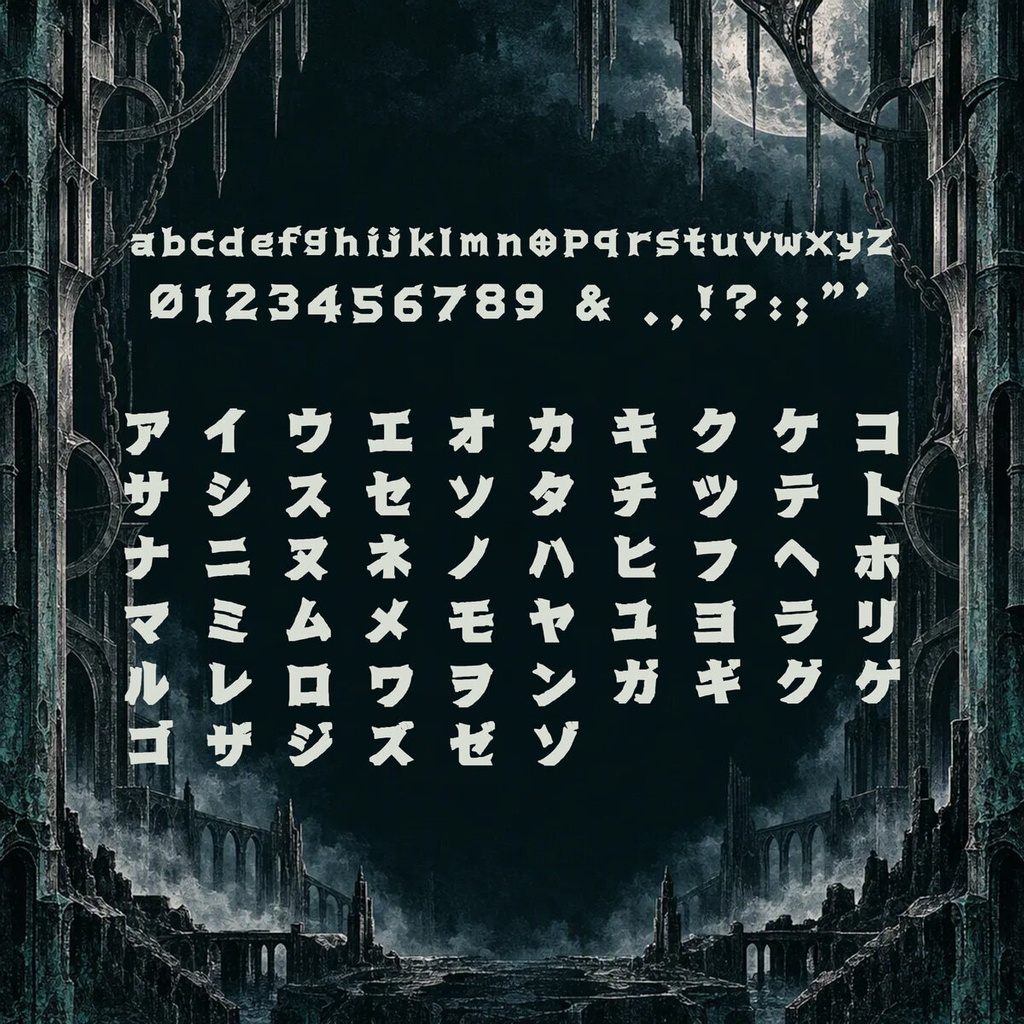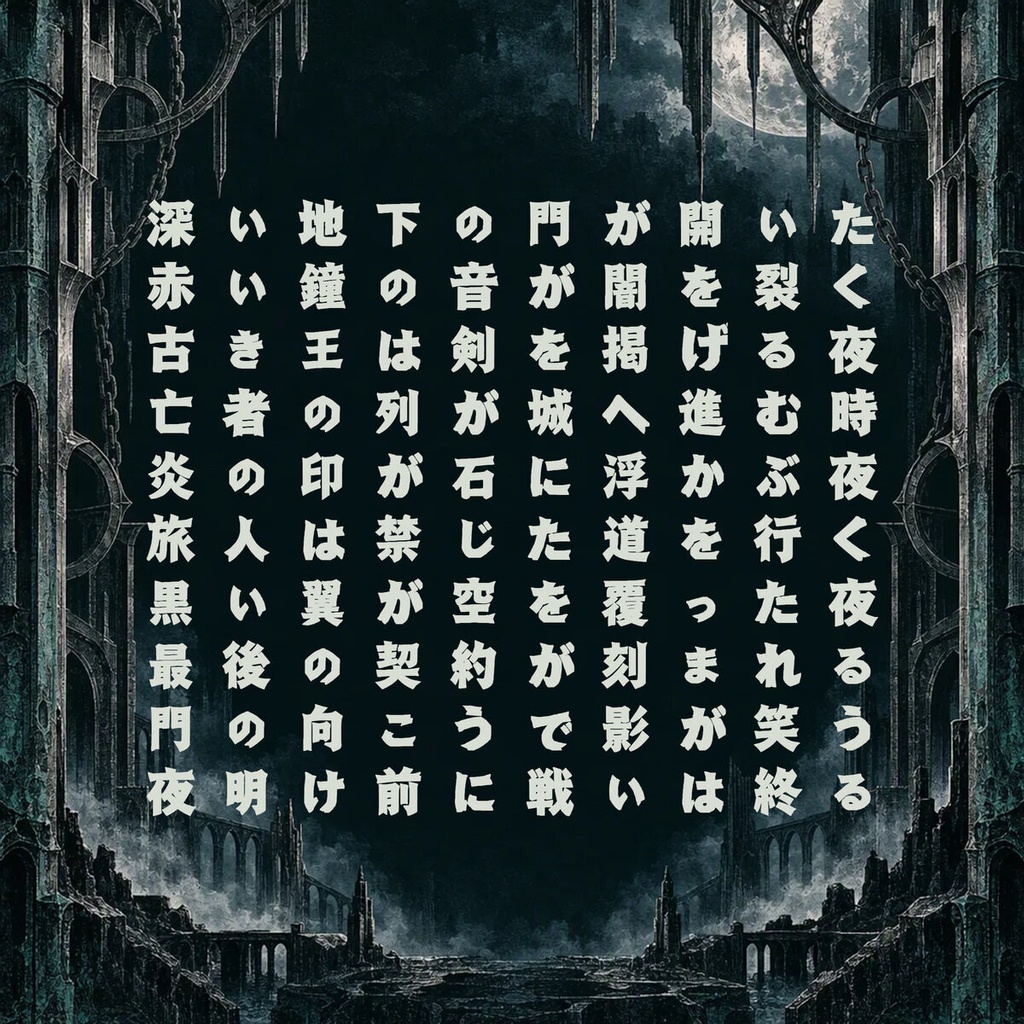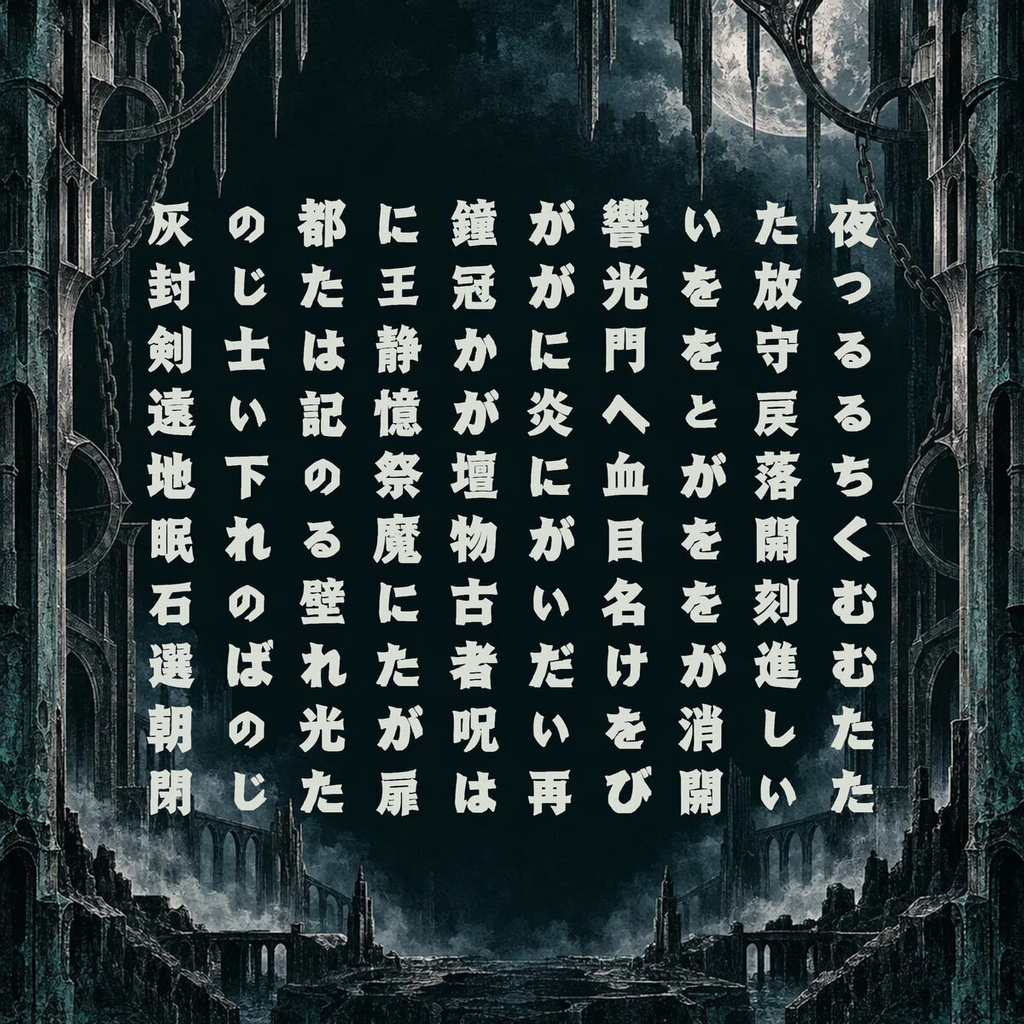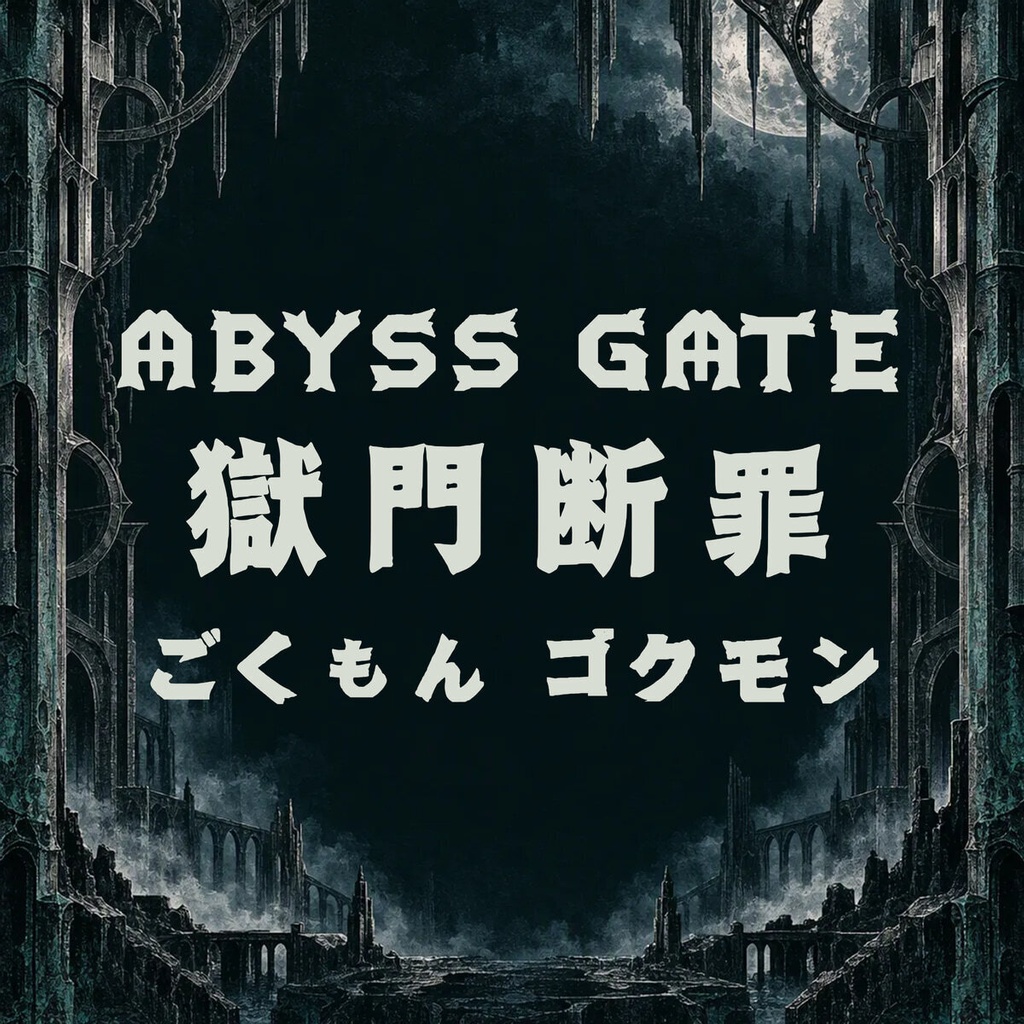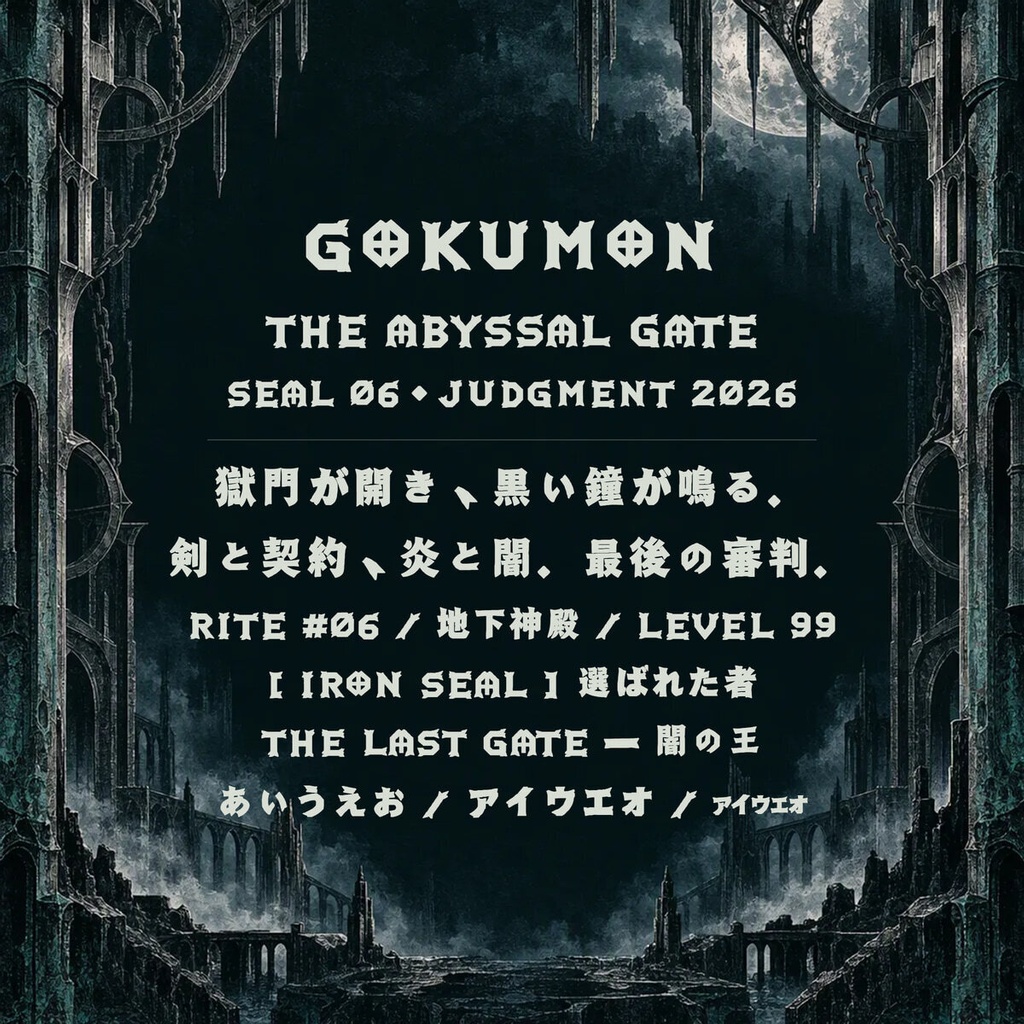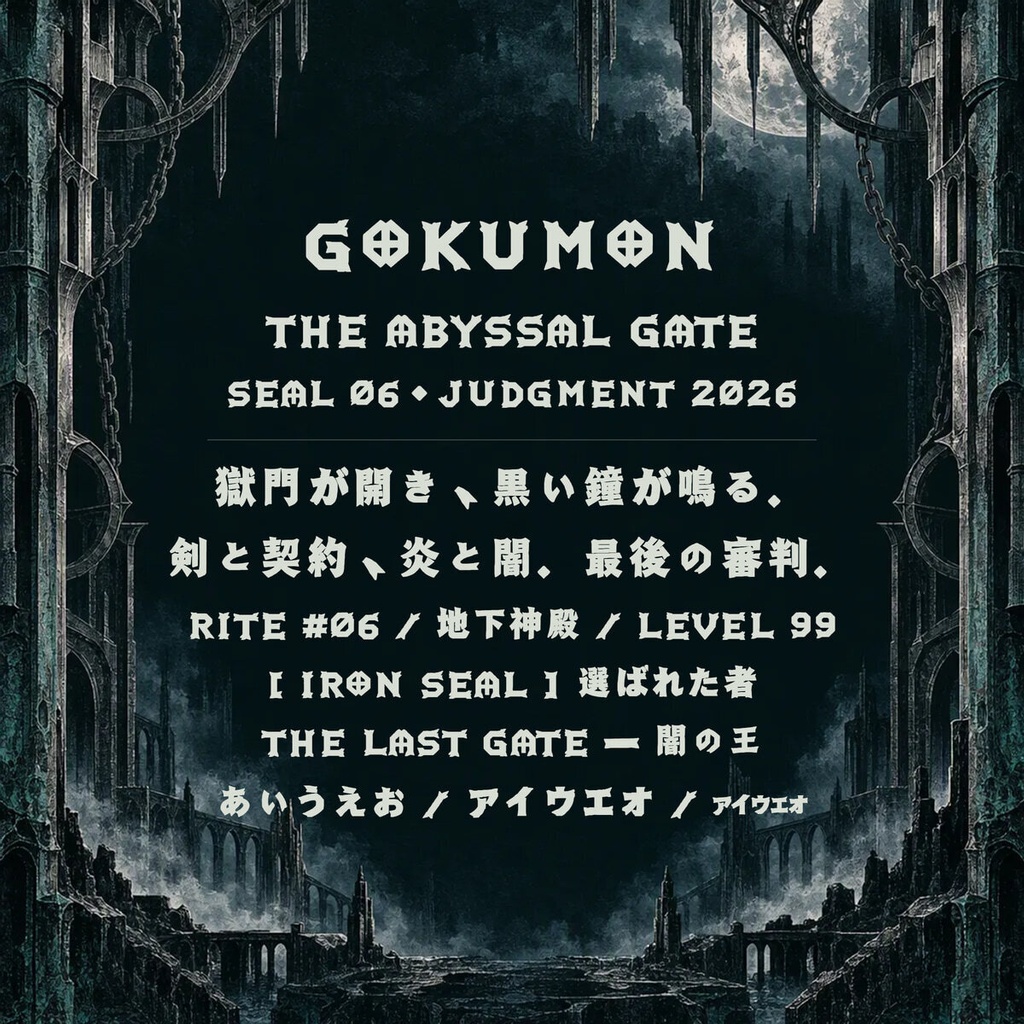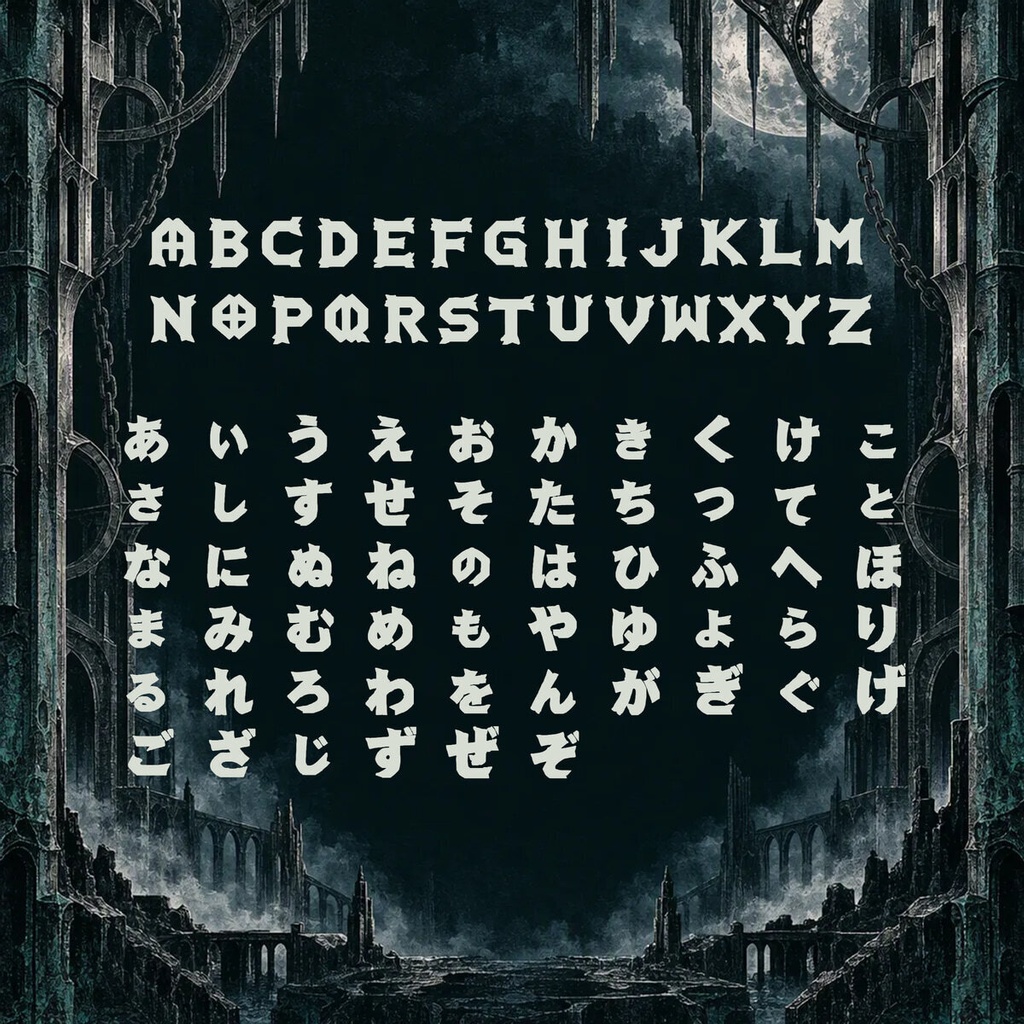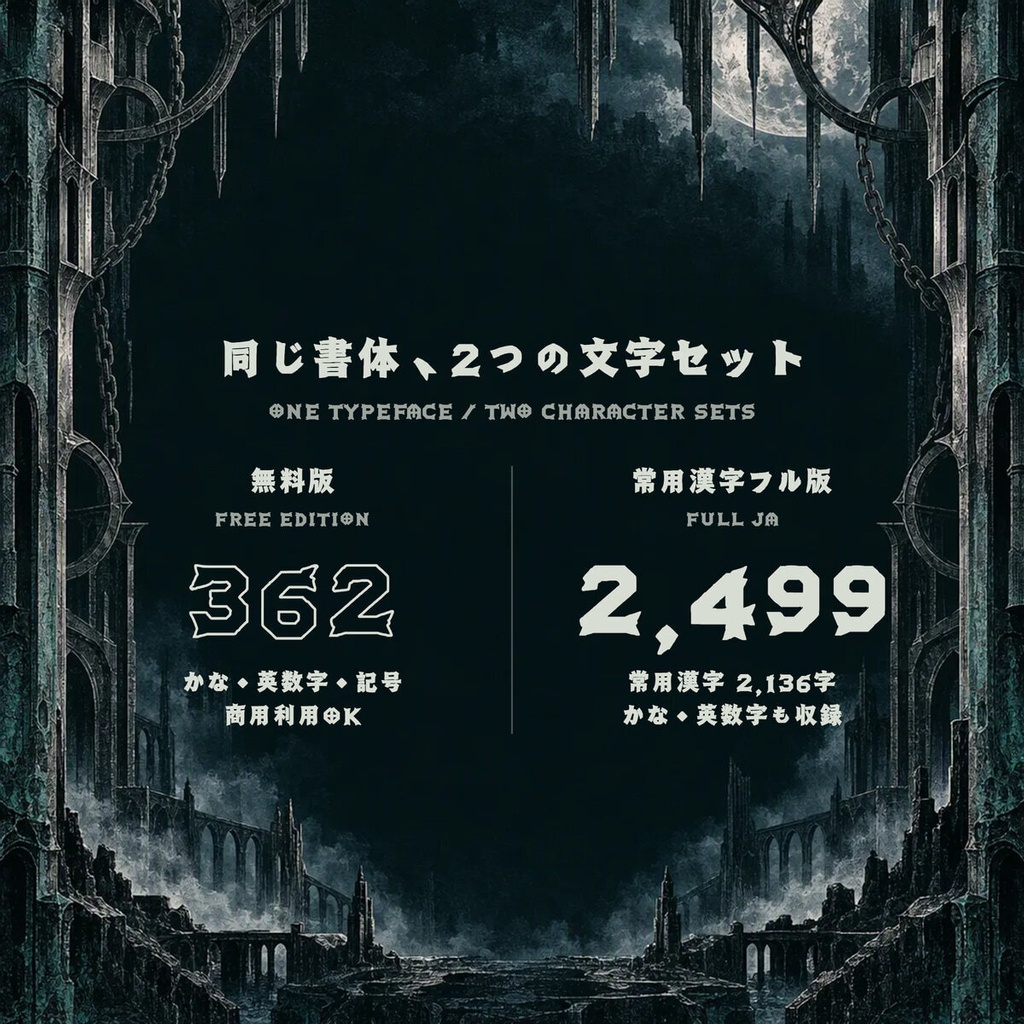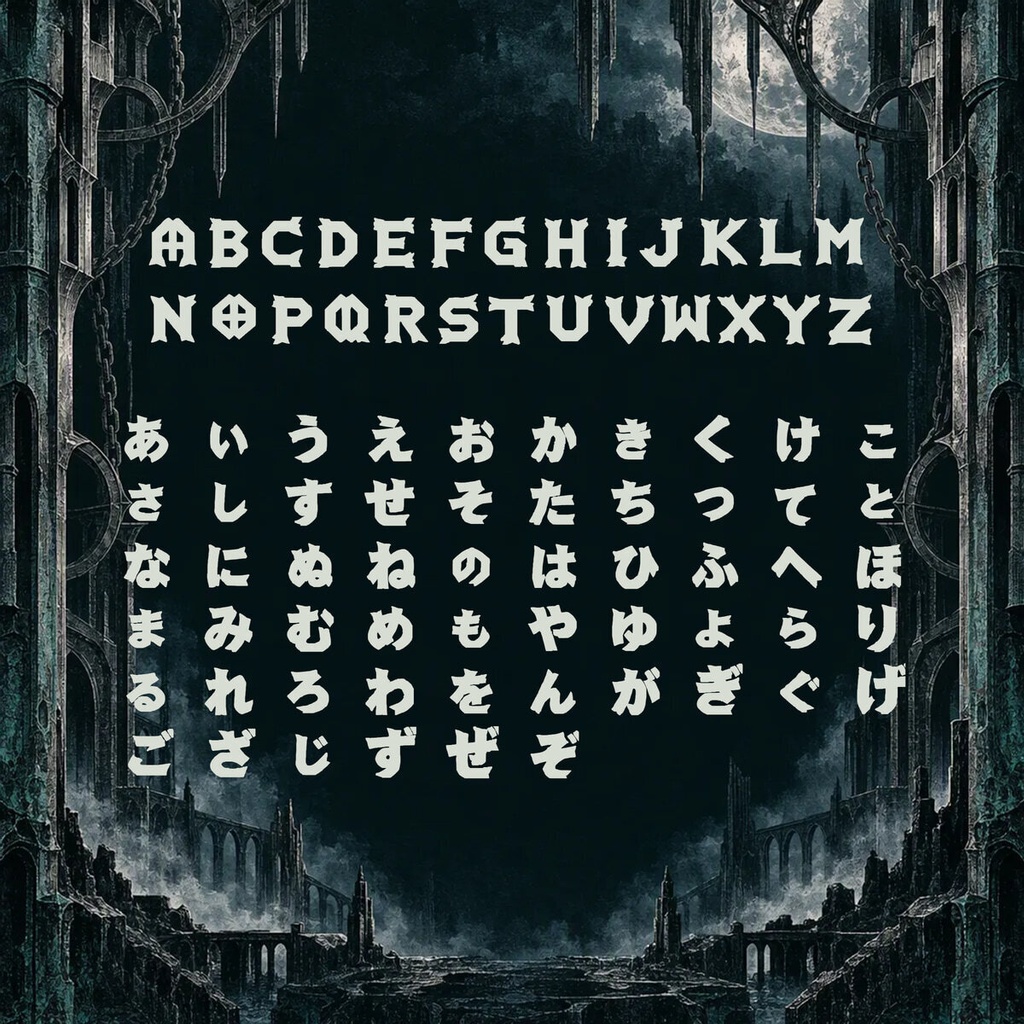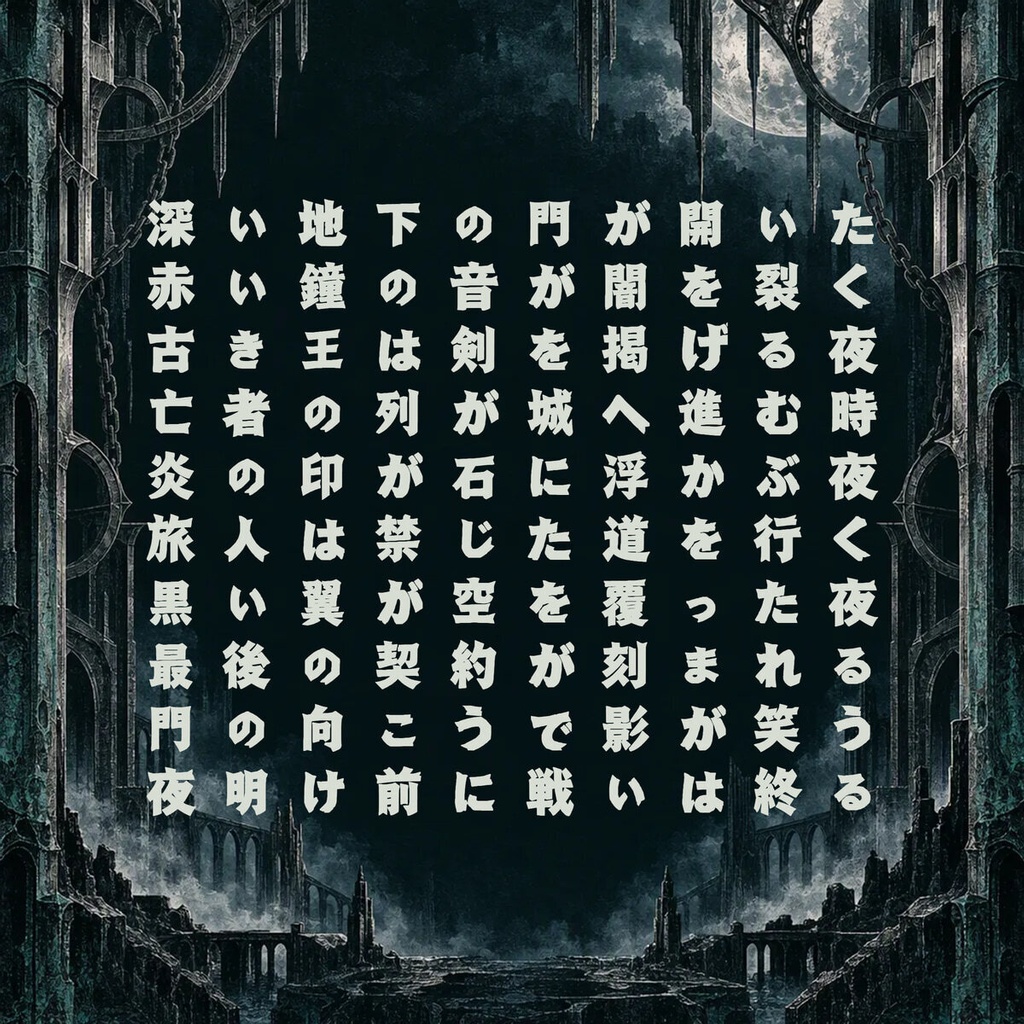
獄門 Gokumon【フォント】 — 十字封印と二股の刃先を備えた重厚書体|常用漢字2,136字
十字封印と二股の刃先を備えた、冥界の門を思わせる重厚なディスプレイ書体です。 A monumental dark-fantasy display face forged with cross-seal counters and forked ironfang terminals. 【用途 / Use】 RPG / ホラーゲーム / TRPG / タイトルロゴ / メタル・ダークウェーブ For RPGs, horror games, TRPGs, title logos, metal, and darkwave artwork. 【常用漢字フル版 / Joyo Complete】 常用漢字2,136字を完全収録し、ラテン文字・ひらがな・カタカナ・記号を含む全2,437文字を収録しています。半角カナは収録していません。 Includes all 2,136 Joyo kanji and 2,437 characters total, including Latin, hiragana, katakana, and punctuation. Half-width kana are not included. 2437文字 / characters 【関連する収録版 / Other Edition】 ラテン文字・かな・記号を収録したスタンダード版もあります。 The Standard edition includes Latin, kana, and punctuation. ▶ スタンダード版 / Standard: https://mojiworks.booth.pm/items/8840453 【フォント仕様 / Specification】 バージョン / Version: 1.0.1 形式 / Format: TrueType (.ttf), Web (.woff2) 対応環境 / Platform: Windows, macOS, web browsers 収録字一覧 / Character list: CHARSET.txt 同梱 / Included: font files, README, LICENSE, character list, portfolio PDF, product previews. 【利用規約 / License Summary】 個人・商用利用可。1ライセンスは購入者1名に適用されます。 Personal and commercial use is permitted. One license covers one purchaser. 印刷・動画・ロゴ・グッズ等の静的成果物、および購入者が運営するサイトでの同梱WOFF2の利用が可能です。 Static output such as print, video, logos, and merchandise is permitted. The bundled WOFF2 may be used on a website owned or operated by the purchaser. ゲーム・アプリへの組み込みは、利用者が生のフォントを抽出できない形式に限ります。生のフォントを同梱する場合は別途ライセンスをご相談ください。 Game/app embedding requires protection against extraction of the raw font. Contact us for a separate runtime-embedding license when shipping raw font files. 標準ライセンスは1製品・1サイトあたり年間約100,000ユーザーまで。従業員50名超の組織を含む大規模利用は要相談。 Standard coverage is approximately 100,000 users per product/site/year. Larger use and organizations with more than 50 employees require an extended license. フォント本体の再配布・販売・貸与・変換・グリフ抽出・派生フォント制作・生成AI学習やスタイル参照は禁止です。 Redistribution, resale, lending, conversion, glyph extraction, derivative fonts, and generative-AI training or style reference are prohibited. 完全な利用条件は同梱の LICENSE.txt / LICENSE.jp.txt をご確認ください。 The bundled license files are authoritative; consult them for the complete terms. 【ほかのフォント・カスタム制作 / More Fonts and Custom Work】 フォント一覧、オーダーメイド書体、文字追加、拡張ライセンスのご相談はこちら。 Browse our catalog or contact us for custom typefaces, added characters, and extended licenses. https://mojiworks.booth.pm/